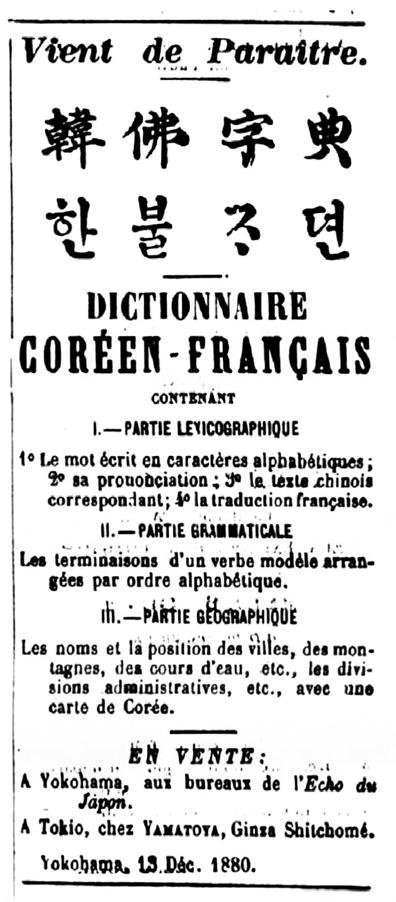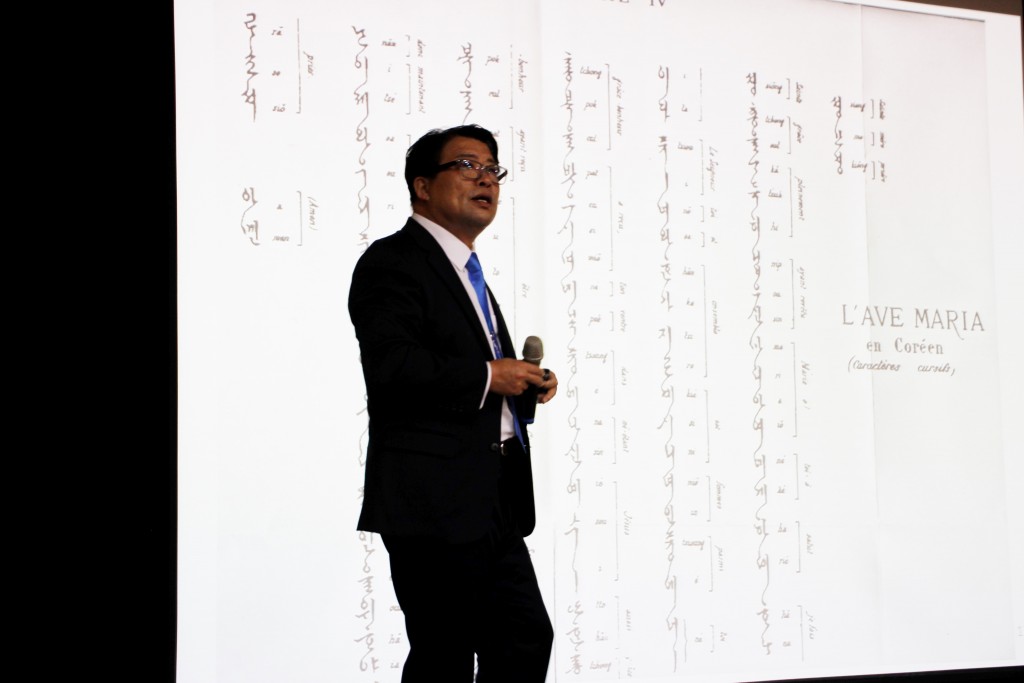
<한글 활자의 탄생 1820~1945> : 전세계를 찾아 헤멘 한글 활자의 기록
<한글 활자의 탄생 1820~1945>은 조선 후기부터 일제강점기 동안 만들어진 한글 활자와 한글 활자를 제작한 인쇄소, 한글 활자의 타이포그래피 특징 등을 정리한 책이다. 저자가 12년 동안 전 세계 40여 개국에 흩어져 있는 한글 활자의 기록을 찾아 직접 원본을 확인하고, 분석해 기록했다.
우리나라 근대 활자사는 비어 있다?
실증적 고증으로 복원한 한글 활자의 역사
조선 후기부터 일제강점기의 시기는 우리 민족에게 암흑기와 같았지만, 민족의 독립운동을 위해 『독립신문』이 창간되고, 한글을 전용으로 사용한 신문들이 창간된 시기이다. 또한 한글 활자 공모를 통해 활자를 개발하는 등 한문 문화에서 한글 문화로 바뀌는 문자 혁명이 이루어진 시기였다. 조선에 선교를 위해 발 디딘 서양 선교사들은 자국의 지원을 바탕으로 한글 문법서와 한글 번역 성경 등을 출간하고, 이 과정에서 한글 활자들을 개발했다. 그동안 『훈민정음』 창제 이후부터 만들어진 한글 목활자, 금속활자 등에 대한 연구들은 많이 있었지만, 근대 시기 만들어진 한글 납활자에 주목한 연구는 거의 없었다.
국립한글박물관 개관위원장을 지낸 홍윤표 선생은 이 책의 추천사에서 “근대 시기의 한글 납활자에 대해서는 아직 이렇다 할 연구 업적이 없었다. 납활자 이전의 금속활자나 목활자, 도활자 등에 대해서는 깊이 있게 연구되어 온 것과는 사뭇 다른 양상”이라며 “한글 납활자에 관한 초기 자료들이 국내보다는 외국에 더 많이 소장되어 있었기 때문이 아닌가 생각한다”고 지적했다.
<한글 활자의 탄생 1820~1945>은 조선 후기부터 일제강점기 동안 만들어진 한글 활자와 한글 활자를 제작한 인쇄소, 한글 활자의 타이포그래피 특징 등을 정리한 책이다. 저자가 12년 동안 전 세계 40여 개국에 흩어져 있는 한글 활자의 기록을 찾아 직접 원본을 확인하고, 분석해 기록했다. 최초의 시도였고, 관련 연구도 많지 않아 어려움도 많았다. 하지만 한글 활자의 원형을 찾겠다는 일념으로 저자의 고독한 노력은 지속되었다.
이 책이 가치 있는 이유는 단순히 다른 사람들의 주장 또는 의견을 종합하거나 재편성한 것이 아니라 실제로 그 자료를 직접 발견하고 확인하여 자료와 이론과 실험이라는 탄탄한 과정을 거쳐 이룬 학문적 업적이기 때문이다. 일본의 근대 인쇄활자사를 최초로 체계화한 연구자인 고미야마 히로시 사토타이포그래피연구소장은 “한국 최초의 근대 활자사에 대한 연구”라고 평가했다. 근대 시기 만들어진 한글 납활자뿐만 아니라 우리나라의 근대 출판 과정, 한글 자형의 변천사 등을 확인할 수 있는 귀중한 자료이다.
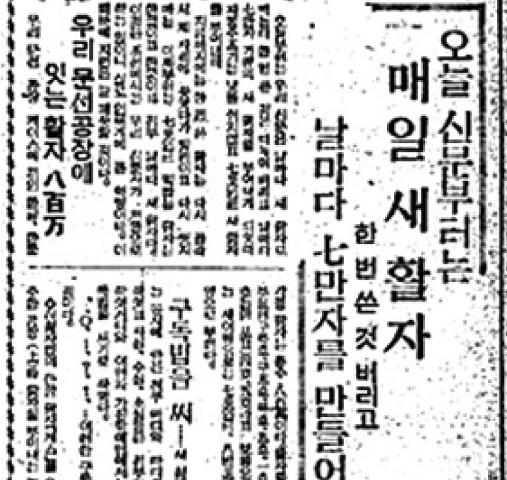
1933년 4월 1일 『동아일보』 신문
활자체를 주목하는 것이 중요한 이유는 시대마다 활자의 변천사가 있는데, 이를 통해 초판본 등을 확인할 수 있기 때문이다. 문학계에서 이슈가 된 김소월의 『진달래꽃』 초판본에 대해 홍윤표 전 연세대학교 국어국문학과 교수는 “활자체에 주목해 『진달래꽃』 초판본을 확인하는 데 도움을 얻었다”고 전했다.
류현국
일본 쓰쿠바기술대학교 종합디자인학과 교수로 재직 중이다. 1991년 도일하여 큐슈예술공과대학 예술공학원에서 박사학위를 받았다. 최근 12년 동안 한글 활자의 원형과 계보를 찾아 40여 개국을 방문했고, 실증적 검증을 통한 연구 결과를 국내외에 논문으로 발표했다. 국제타이포그래피협회(ATypl) 비라틴어부문(Non-Latin sector)의 초빙강사, 뉴욕 타이포그래피 디렉터스 클럽의 상임이사로 활동 중이다. 일본 이와타사와 함께 저시력인과 장애인 및 고령자를 배려해 가독성을 높인 ‘유니버셜 폰트 디자인’을 공동 개발해 발표할 예정이다. 저자는 한글에 관해서라면 아무리 작은 역사의 한 조각이라도 소중히 탐구하며, 한글 활자의 원형을 찾는 것이 더 나은 서체 개발의 시작이라는 사명을 가지고 한글 활자 연구에 매진하고 있다. 『한글 활자의 탄생 1820-1945』는 오랜 시간 고독한 노력을 기울여 온 저자가 처음으로 써 낸 모국어 저작물이다.